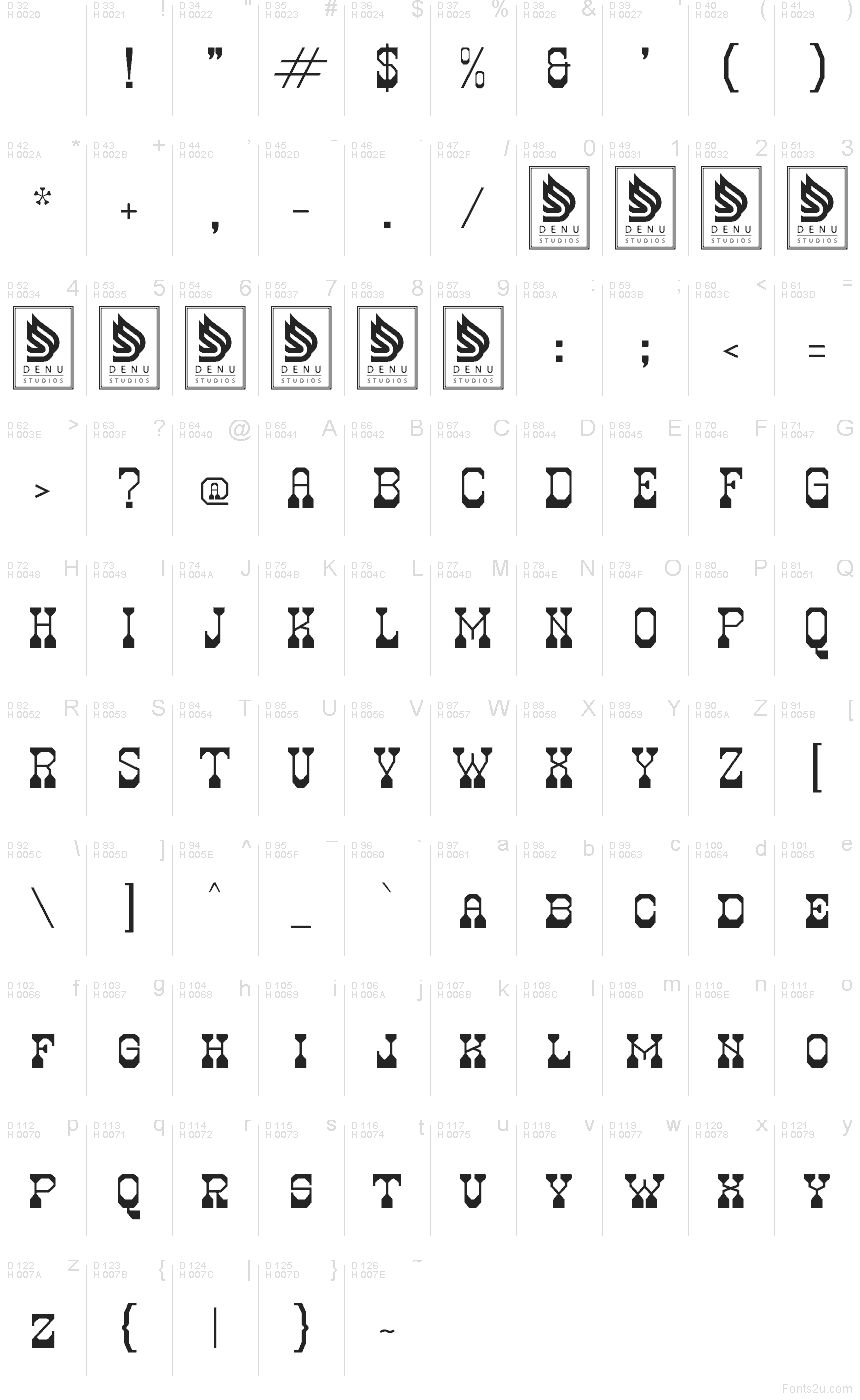
The Gasone de Denustudios es una tipografía display de estilo western gratuita con la actitud desafiante de los antiguos carteles de la frontera. Sus letras están cortadas en formas octogonales y robustas, con esquinas afiladas, trazos verticales partidos y unas muescas llenas de carácter que le dan a las palabras una sensación de tallado, como la de un cartel de saloon, más que la de un simple diseño retro pulido.
Esto convierte a esta fuente gratuita en la elección natural para titulares en carteles, branding de whisky o barbacoa, flyers de festivales, títulos de juegos y empaques impactantes que busquen ese aire polvoriento del viejo oeste americano. También funciona muy bien en textos cortos y logotipos, ya que su geometría cortante y uniones estrechas dan, incluso a pocas letras, esa presencia rotunda propia de la señalética pintada a mano.